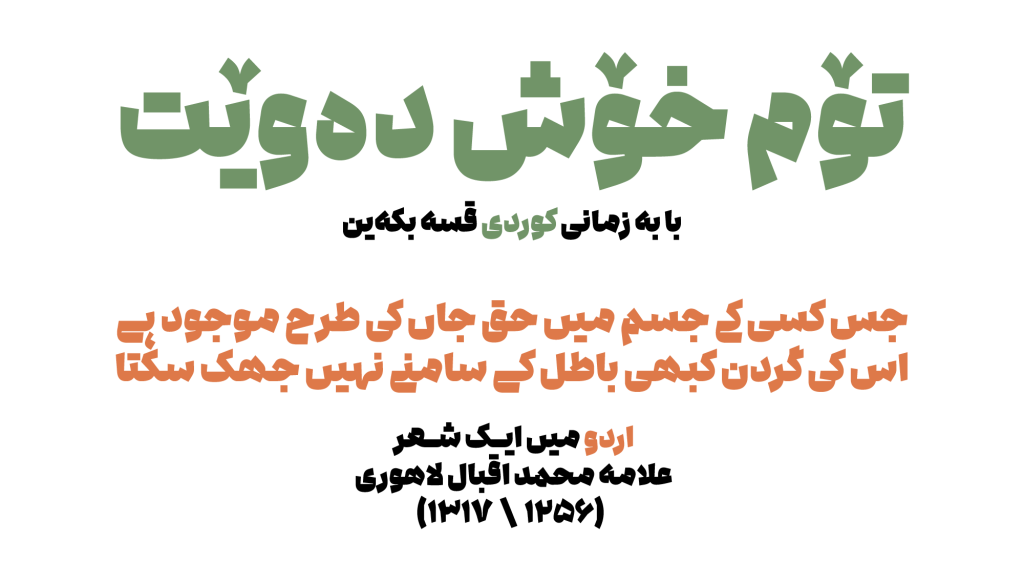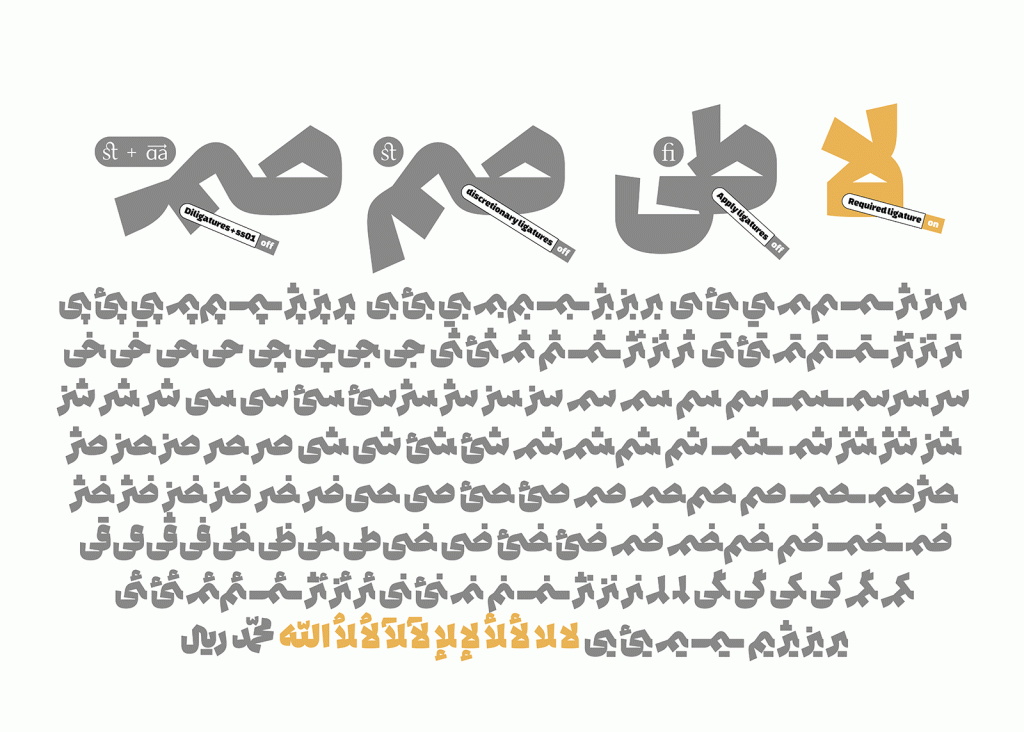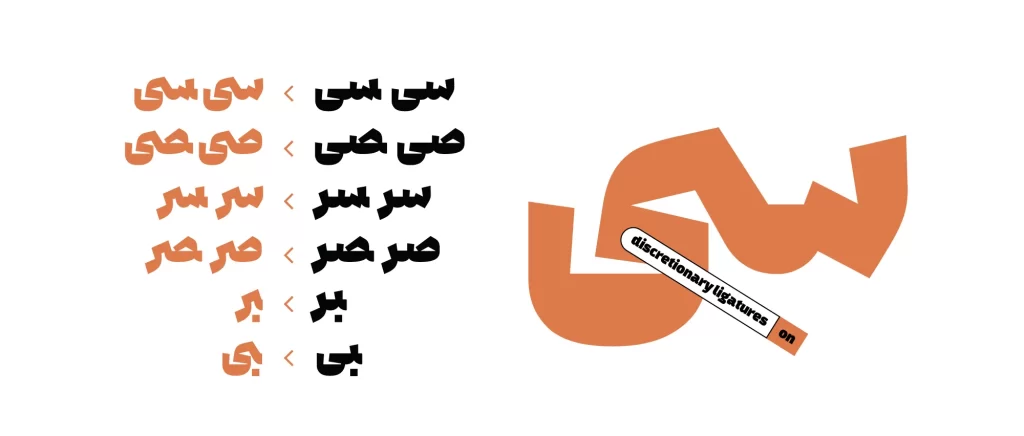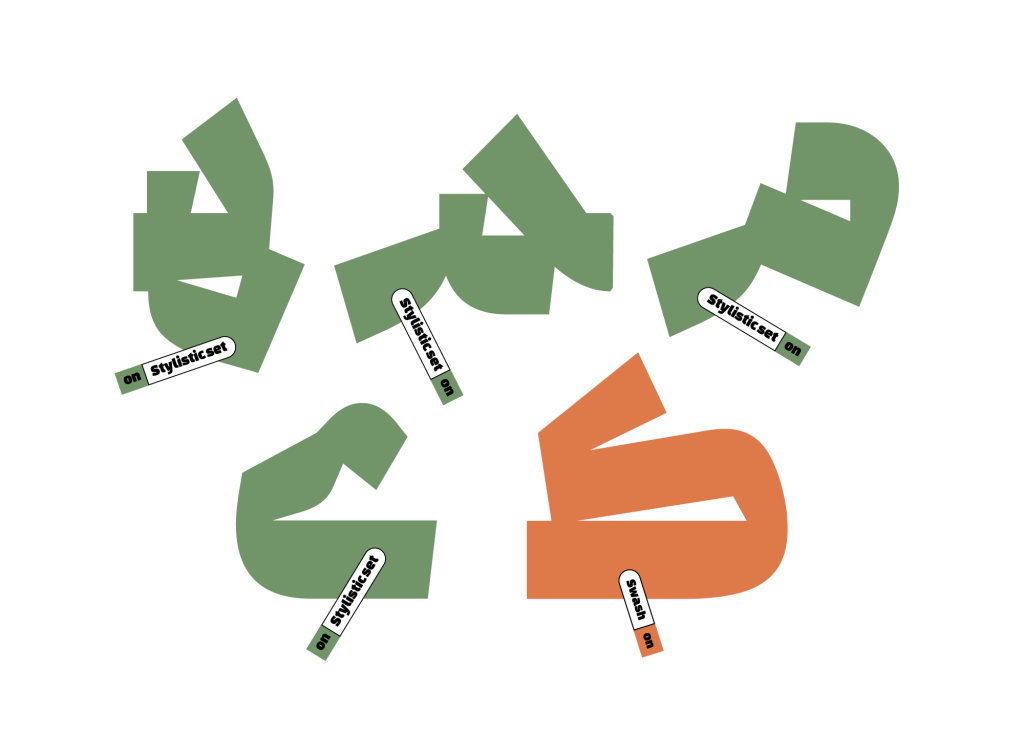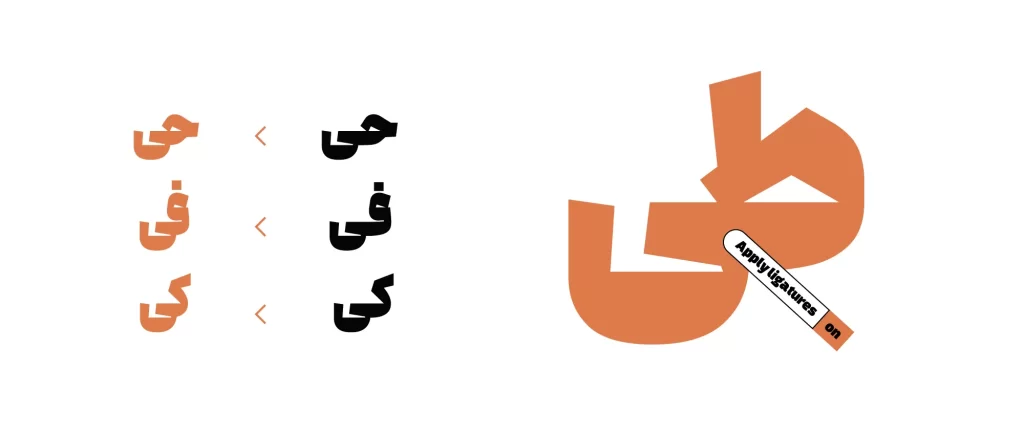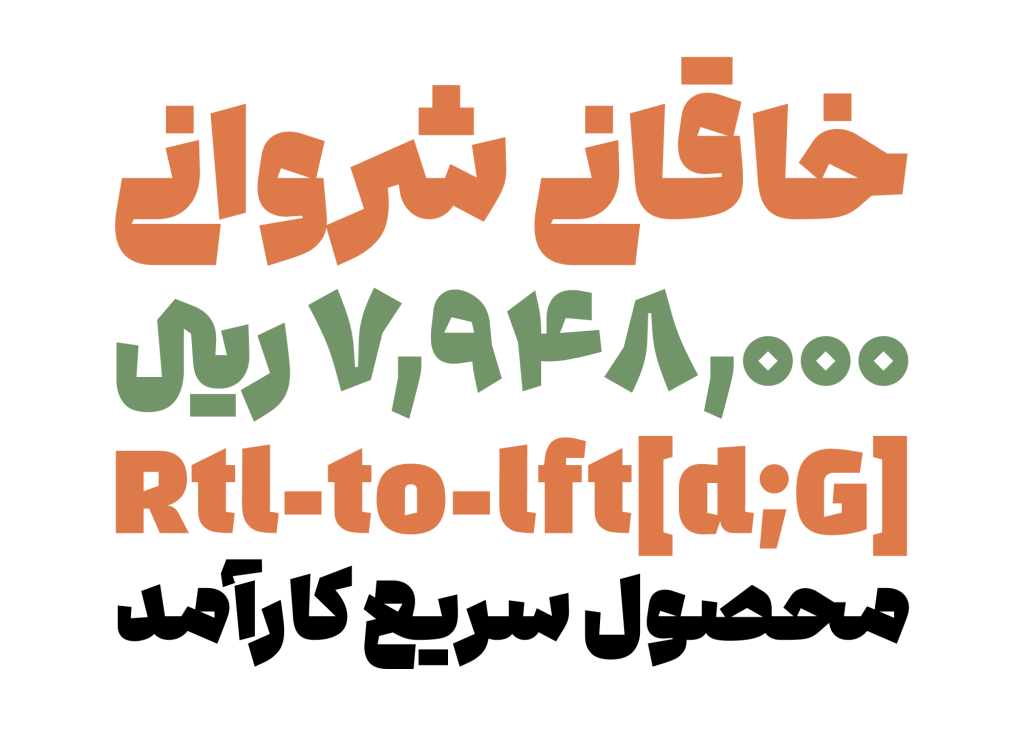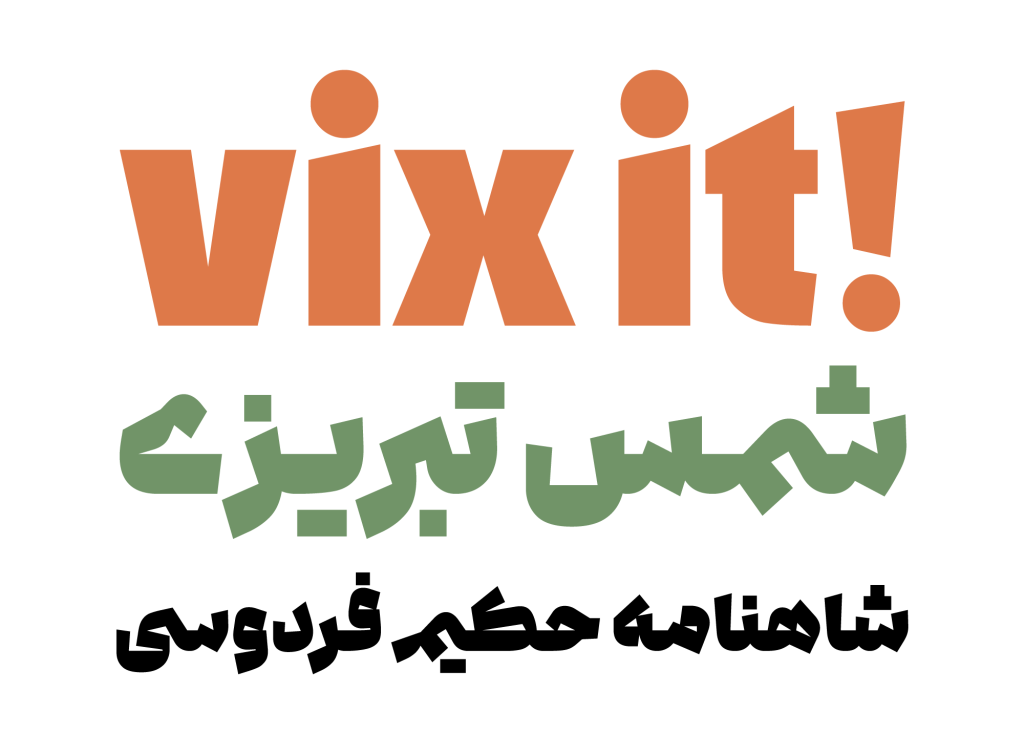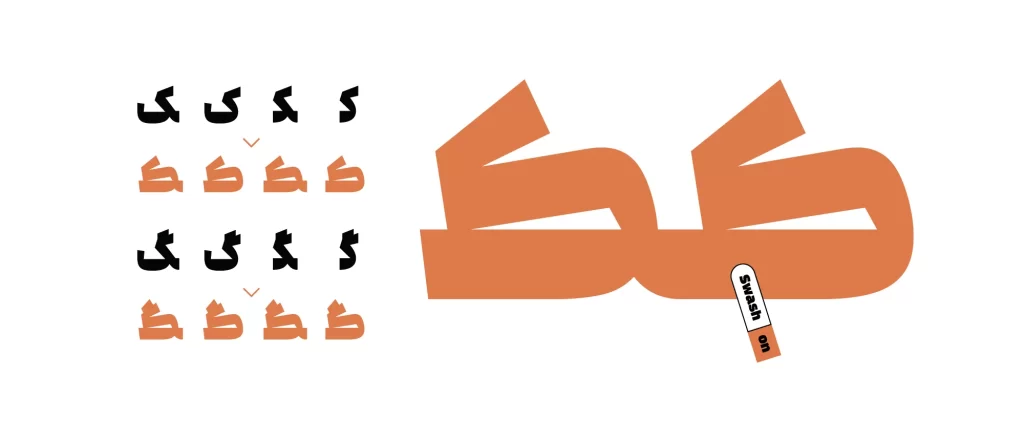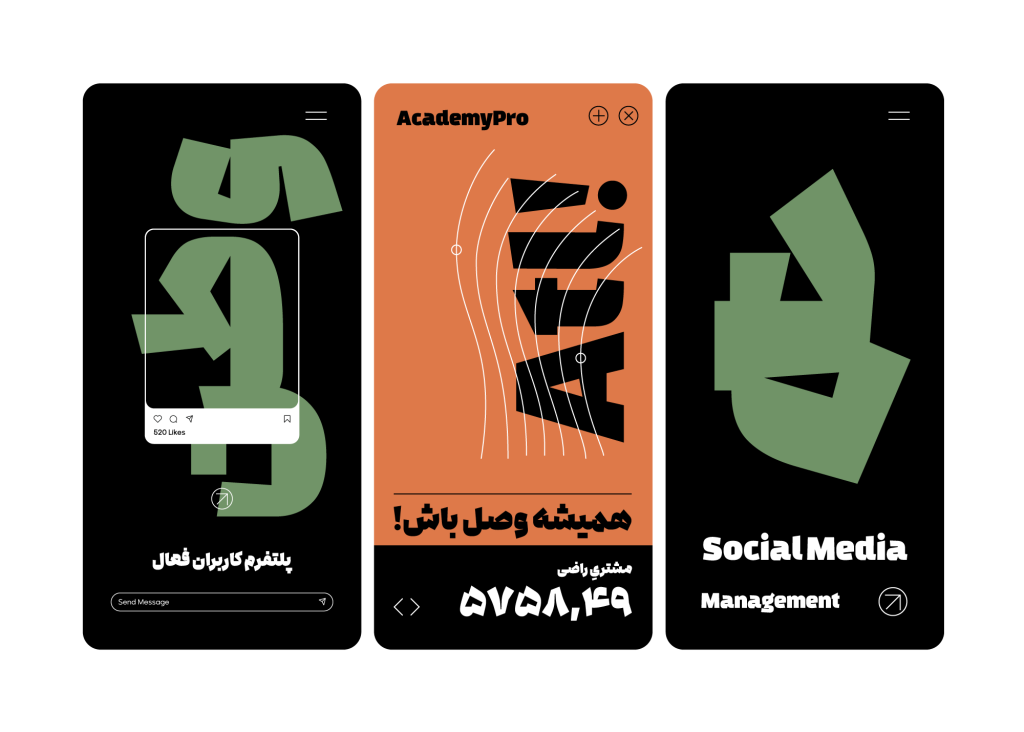
فونت ادامه
فونت ادامه با تلاش ها و زحمات فراوان آقای ناصر خادم طراح ایجاد گردید وی در باره روند طراحی این قلم خاطر نشان می شود که “ نتیجهی تلاشهای من برای مطالعهی جزییات در هندسهی خوشنویسی ایرانی در کلاس استاد دامون خانجانزاده است. با تبدیل اتودهایم به فرمهای سنگین، به مرور این فونت را با هدف استفاده در تیترهای تککلمهای و متنهای کوتاه پیش برده و آن را کامل کردم “.
تله ای برای جذب چشم مخاطبان
با دقت در بدنه و ساختار ادامه می توان دریافت که این تایپ فیس با کنتراست تامل بر انگیز در سطح حالت یکنواختی و رخوت را از چشمان مخاطب می گیرد. دارای زوایای 90 درجه و حتی کمتر در زوایا و گوشه ها می باشد. همچنین پشتیبانی از فرم ها و زاویه های نرم را نیز در بدنه خود د رسطح دارد.
از همین سبب یعنی وجود فرم های تیز و تند در کنار فرم های نرم و منعطف می توان فونت ادامه را قلمی دارای شخصیتی چند گانه در نظر گرفت. تاکید بر فرمهای چشمگیرِ حروف در عینِ توجه به ظرافتهای طراحی در آن در نظر گرفته شده است. یکی از کاربرد های اصلی ادامه را می توان در تیتر ها و عناوین انواع کسب و کارها و استارت آپ ها به شمار آورد.
ادامه با با دارا بودن فرم ها متنوع و شخصیتی چند گانه جسور و بی باک است و جنبه نمایشی و خود نمایی در تار و پود خود جهت جذب نگاه خوانندگان و بینندگان به خود دارد. به عبارت ساده تر می توان گفت این قلم مانند یک تله چشم مخاطب را درگیر خواهد کرد.
پشتیبانی ادامه از حروف جایگزین
طراحفونت ادامه، تعداد زیادی حروف و ترکیبات که میتواند تنوع خوبی در ساختِ تیترها و جملاتِ کوتاه ایجاد کند. برای شما عزیزان در نظر گرفته است از جمله این حروف می توان به «ک» «گ» «ی» «م» «ی» «ه» «ر» اشاره نمود . در زیر تنوع و شکل استفاده از این ترکیبات در تصاویر نمونه آورده شده است.
شایان ذکر است که این قلم برای زبان فارسی و عربی طراحی شده است و زبانهای اردو، کردی و انگلیسی را نیز پشتیبانی میکند.